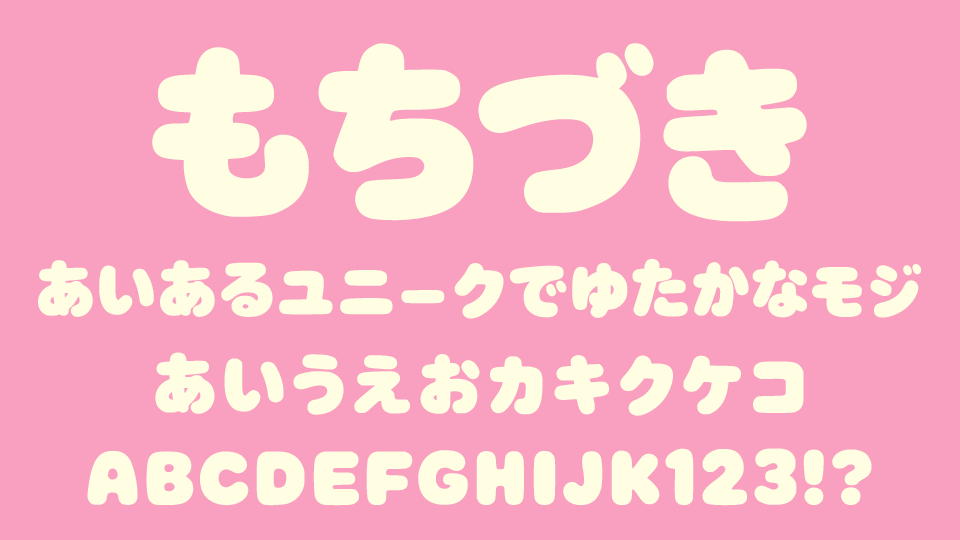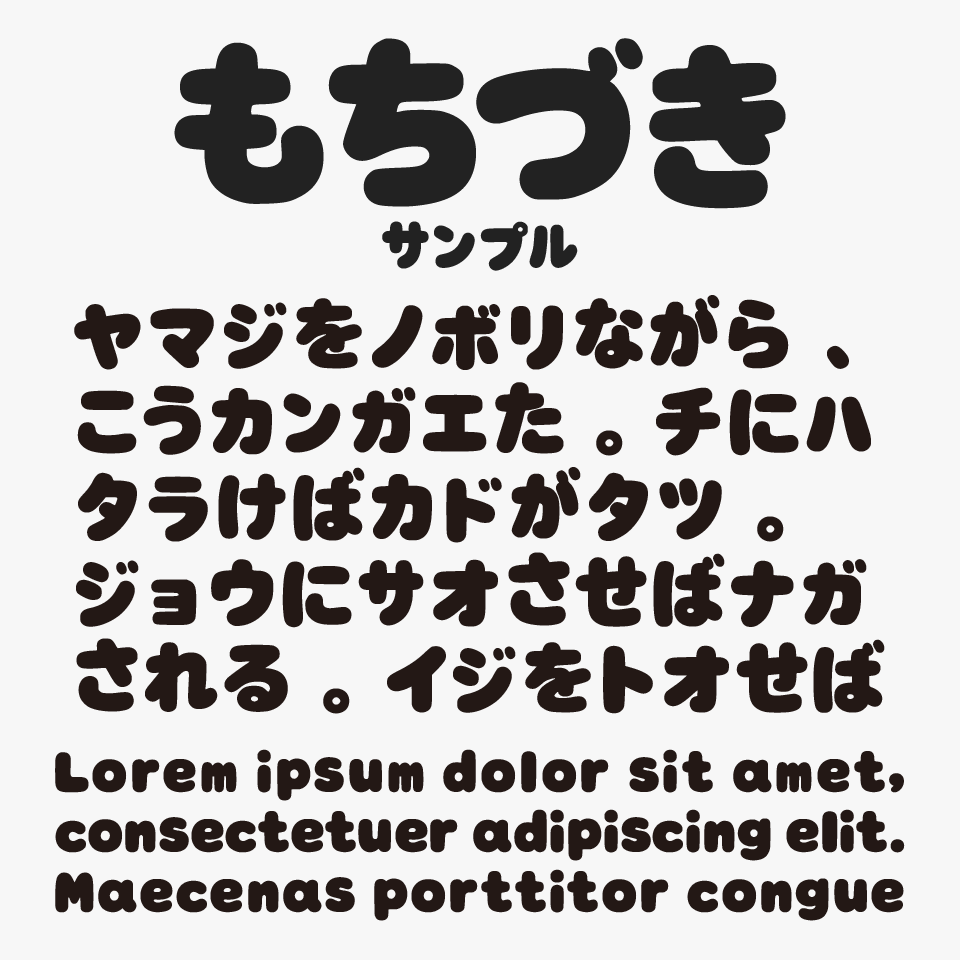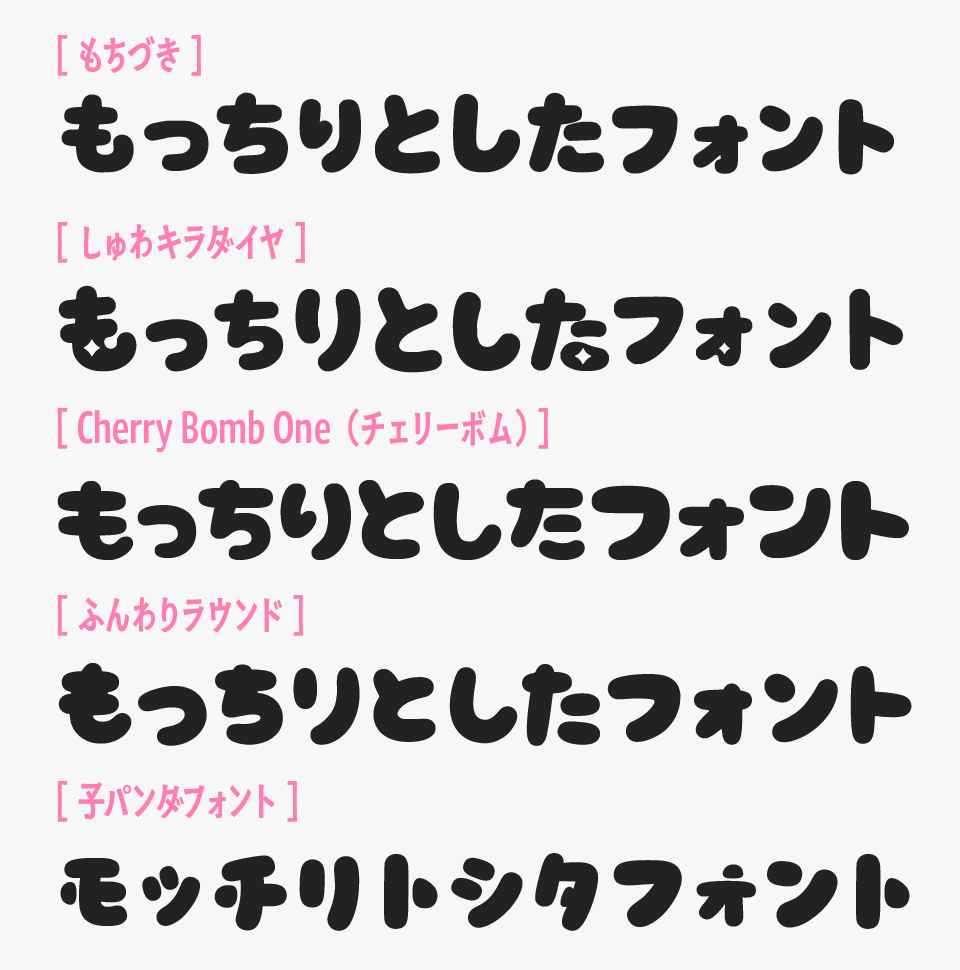
もちづきフォントは、丸みを帯びた太めのもちもちとしたシルエットが特徴的な、やわらかく愛嬌のあるデザインフォントです。
線の太さが均一ではなく、ほんの少し揺らぎを感じる形状によって、甘さのある可愛いぬくもりが伝わってくるようなフォントです。文字全体がふっくらと膨らんだような雰囲気を持っており、やさしく親しみやすい印象を作れるフォントです。
かわいい系タイトルやVtuberのサムネイル、お菓子パッケージ、ポップなバナーなどと相性が良く、見た人の気持ちをふっと和らげるような空気感があります。太めで存在感がありながら、丸いフォルムのおかげで強すぎる印象にならないのもステキなポイントです。
もちづき
もちづきフォントは、ほかの“もっちり”としたやわらかい雰囲気を持つフォントと比較してみると、このフォントは、しっかり丸みがありながらも、どこかきっちり整った印象があるところが特徴です。
比較フォントは「しゅわキラダイヤ」「Cherry Bomb One(チェリーボム)」「ふんわりラウンド」「子パンダフォント」と使用していますが、どのフォントもとても可愛らしくいので、あわせてチェックしてみてください。
もちづき(望月)フォントと、「しゅわキラダイヤ」「Cherry Bomb One(チェリーボム)」「ふんわりラウンド」「子パンダフォント」を比較
収録文字は、ひらがな・カタカナ・アルファベット・数字・記号が収録されています。
ひらがな○
カタカナ○
漢字×